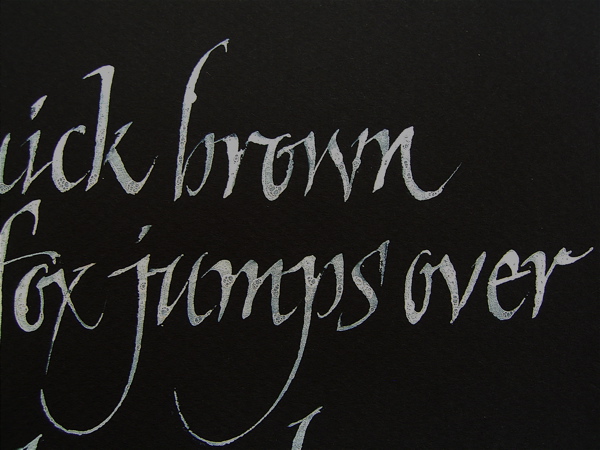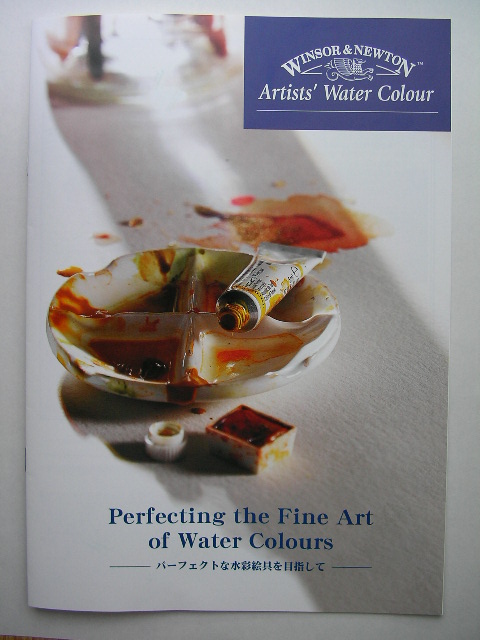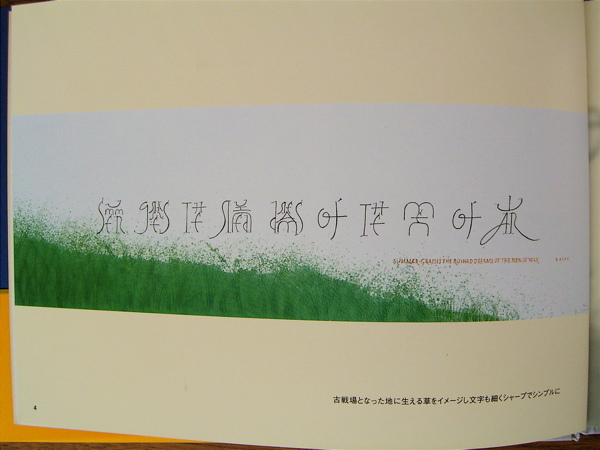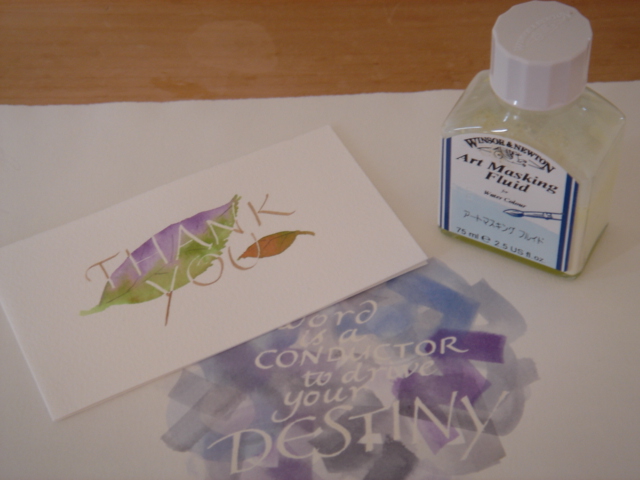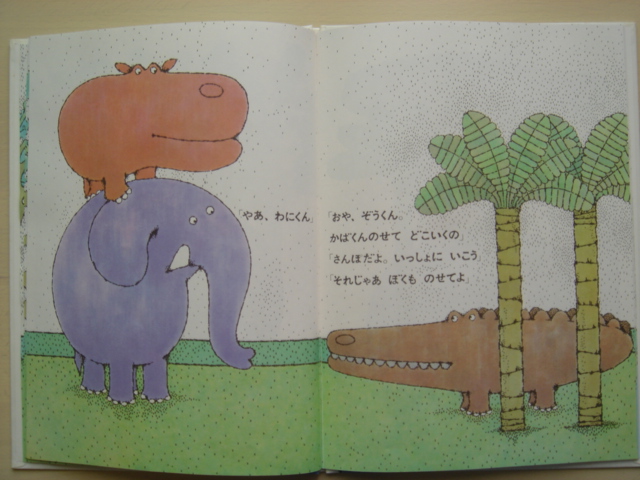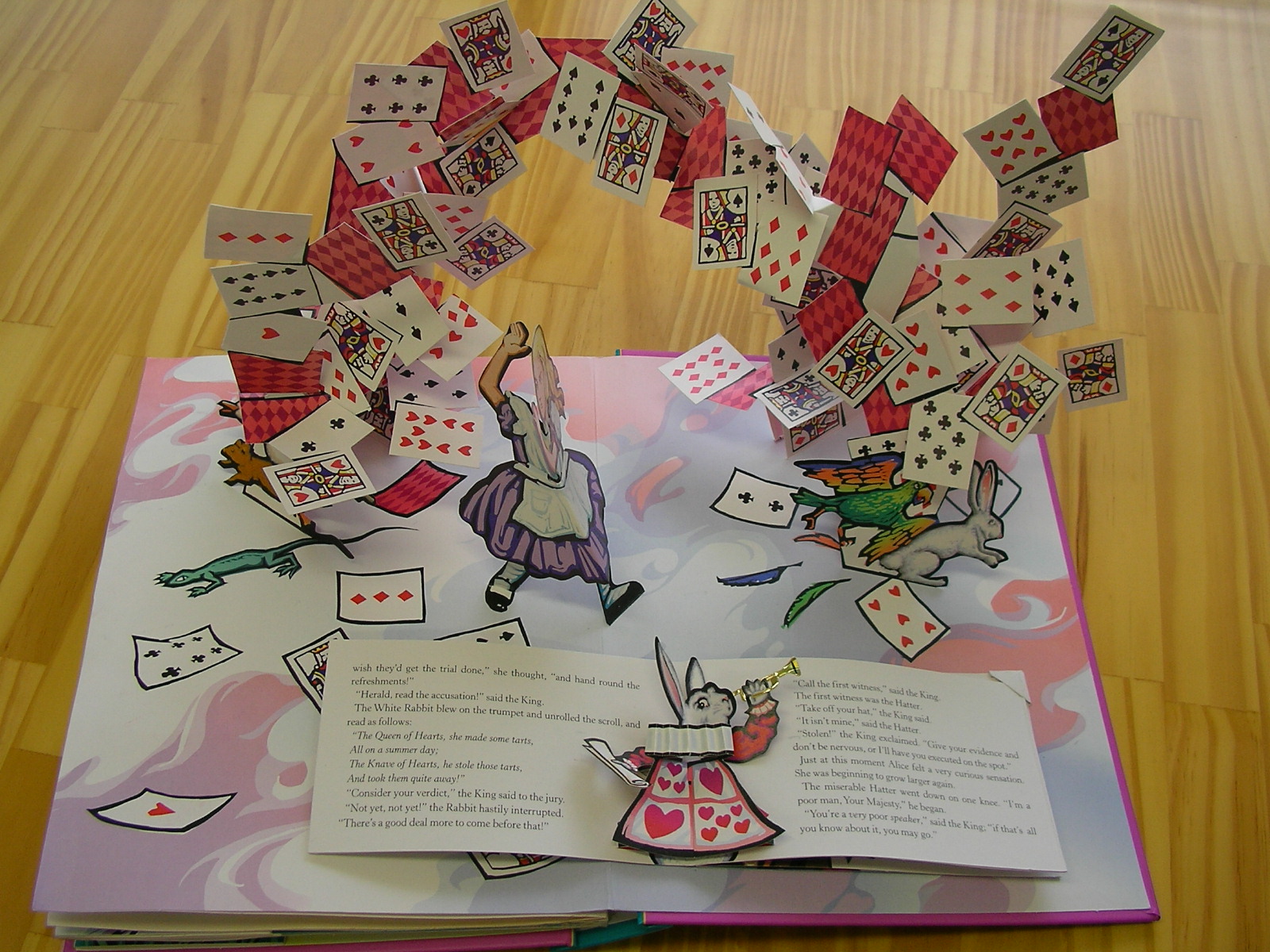
アルファベットのふきん
自由が丘のお店は3階でお食事とお茶ができ、1階、2階がショップになっています。帰り際に2階に寄り道。そこで見つけたのが、籐のかごにすました顔で並んでいたアルファベット柄のふきんです。少し重たい感じの書体ではありますが、何か可愛くて…つい購入してしまいました。いけない…また文字好きの癖が出てしまいました。
モジにかかわるある風景
スイスのサンモリッツという町で見かけたある風景…。
最初に通りかかったときは、おじさん大きなアルファベットと格闘中…。なるほど、こんな構造、こんなからくりだったのか…。ブラブラと風に揺れているB,T,Aがかわいらしい。おじさんのお取込中にハイ、パチリ
町の散策もだいたい終わり帰り道…。おじさんの姿は既になく、きれいなスペースでアルファベットが並んでいました。お店もオープンしていました。メデタシ、メデタシ!
町にはいろんな書体のアルファベットが自然な姿でいろんな場所におさまっていました…。やはり地元のモジなんだなぁ…と実感!その町の建物や雰囲気と合っていて…なんかいい感じでした。
ぞうくんのさんぽ
「ぞうくんのさんぽ」はロングセラーの絵本です。子どもが小さいときに本屋さんでみつけたのですが、店頭でおおおっと喜んでしまいました。
なぜならこの絵本は活字ではなく、レタリングなのです。このひらがなが並んだ感じがとってもかわいくて即購入。
せりふものんびりとした言い方の繰り返しで小さい子のハートをつかんでいるんだろうなあ。
「さんぽだよ、いっしょにいこう」とか「いいとも、いいとも」とか・・・人のよいぞうくんのゆったりした話し方に
ぴったりの文字たちなのです。
絵のほうも動物の色がさりげない渋さで親子共にお気に入りの1冊です。
英語版も出ているようなのです。そちらの文字はどうなんでしょう、どなたか読んだ方いらっしゃいますか?
白墨液
白のインクや絵の具はいろいろとありますが、先日白墨液というのを発見しました。開明という書道のメーカーから出ています。カリグラフィーでは、色の濃い紙に白で書く事はよくありますが、書道で白を使うって見た事がないなぁ・・・・と思っていました。
でも・・・なんだかどこかで見覚えがあるような・・・・・
そうだ!見た事ありました!ありました!
よく旅館の入り口の看板に「歓迎 モジトル御一行様」って書いてある、アレですね!
よく振ってお使い下さいと書いてあるので、思いっきり振ったら、アワだらけになってしまいました。そのまま書いたら、なんと!バブルの形がそのまま文字の中で乾いて、とても面白いことになりました。普通の練習用の黒インクでもアワが立ちますが、黒だから書いても目立たなかったのでしょう。画像ではよくわからないかもしれません。拡大してみてください。
ハクボク液と読むのかと思ったら、しろずみ液とフリガナがふってありました。黒の紙では、少し下が透けますが、黒板や鉄板、プラスチック板、ガラス板にものります、と書いてあります。いろいろと試してみましょう。
東西融合
ところで芭蕉の俳句で 夏草や兵どもが夢の跡 というのがありますが、画像はそれをFusion Letterとして、アルファベットを漢字のように表現した松木久美子さんの作品です。
英文訳は、Summer grasses the ruined dreams of the men of war です。
東西融合の不思議な形。どちらかと言うと漢字というよりハングル文字にも見えますね。
ひとつひとつをよ〜く見ると、アルファベットが裏返しになっていたり、セリフが強調されていたり、大文字と小文字が一緒に使われていたりと、漢字の雰囲気を表すためによく工夫されています。
アルファベットと日本の文字を融合させた文字のさきがけとしては、遠山由美さんのDual Letterが有名ですが、このFusion Letterはあくまでも漢字の構成に当てはめたブロック文字として書いた創作文字なのだそうです。
マスキング
マスキング液は乾くとゴム状になって紙の白色を絵の具から守ってくれます。上からおいた絵の具類がかわいたらゴム状になったものをはがすわけです。
乾いて固まったマスキング液をピリピリとはがすのが快感なのか・・・
淡い色をのせるのでたいした効果が出ないとわかっていてもやっているのでこれはもはや習慣?
私個人はウィンザーアンドニュートンのマスキング液が好みです。色が淡い黄色なので白い紙にのせたときに見にくいのですが細いラインでもきれいに抜けるように思います。ほかにはミツワの製品がポピュラーで大抵の画材店にあると思います。
はがすときは紙を傷めないようにそっと、ラバークリーナー(ペーパーセメントなどをはがすゴム)などを使って・・・と
教えられたのですが実際は指の腹でこすってボロボロっと落としています。断然速いし、水彩に限って言えばざらついたりはしません。
子どもでも楽しめるマスキング、出来上がりを楽しみに今日も塗り塗りしています。
WINSOR&NEWTON Artists' Water Colourパンフレット
絵の具をはじめ画材というものは、持っているだけで楽しいものですよね。 カリグラフィーを始めて、画材屋に足を踏み入れてからはまっている人も多いのではないでしょうか。海外のカリグラファーも来日の際、日本の画材屋の棚にずら〜っと並んだ様々なブランドの色とりどりの絵の具に感激するほど、日本の画材は、充実しているようですし、情報いっぱい、楽しく、時間を忘れてしまう空間です。
さて、画材については、インターネット検索や書籍で、情報、知識を得ることができますが、メーカーが作っている紙のパンフレットも、有効で、きれいな印刷、ご自由にお持ちくださいというとても魅力的なものです。 その中で、WINSOR&NEWTON Artist's Water Colourのパンフレット、Perfecting the Fine Art of Water Coloursーパーフェクトな水彩絵の具を目指してーは、水彩絵の具を世界で初めて世に出したW&Nならではの充実したパンフレットではないでしょうか。製造方法、顔料についての詳細、堅牢度に関するデータ、カラーチャート、メディウムと盛りだくさんの14ページです。カドミウム顔料および代用顔料や新しい絵の具、改良された絵の具、製造中止になった絵の具の理由、長所がわかる一覧は、納得のページです。隅まで読めば、絵の具の知識倍増でしょう。
山田正亮展
会期終了間際の山田正亮の展覧会を見に、府中美術館へ行きました。
山田正亮は、日本の抽象絵画のひとつの到達点を築いた、とパンフレットには書いてあります。
私は今まで彼の絵は見た事はありませんでしたが、会期間際に行けて本当によかったです。
展覧会では、静物(Still Life)の具体的な形が徐々に失われ、面からなる作品(Work B)へと変化し、そして彼の代表するストライプの絵画(Work C)へと移って行くその変遷がよくわかりました。
私が見に行ったその日、ものすごい雷雨で土砂降りだったせいもあって、広く静かな会場に、私以外に人はほとんどいませんでした。
静かなはずなのに雨の音がかすかにする会場。ストライプのいくつもの大きな作品に囲まれ、それらの前に立って平行な線と色の繰り返しを見ていると、なんだかソワソワ落ち着かないような、それでいてずっと見ていたいというような、不思議で面白い感覚。
雨が止むまでミュージアムショップで時間をつぶし、雨上がりの少し涼しくなった中帰宅しました。
展覧会の印象は、その展示物だけではなく、天候とか人ごみとか、その時の状況によってずいぶん変わるのだろうなぁーと思った一日でした。
ストライプの絵は、かなり長く心に残りそうです。
不思議の国のアリス ポップアップブック
本棚に入れておくだけではもったいない、みんなに見せたくなる(見せてます!)自慢の絵本、不思議の国のアリスのポップアップブックです。
大人も子供も、開いた人は誰しも、思わずにっこりしてしまう、ハッピーになれること間違いなし。おいしいものに出会ったときと同じですね!
Robert Sabudaのポップアップは、どのページも芸術的、なかでもこのトランプのページは、感激!絶対買うぞ気分にさせるでしょう。(事実、私は、買ったわけです!) しかし、よくまあ、このようなことができるとは、手にして、目にして感激するだけでなく、感心しきりです。これを見る人は、前からだけでなく、いろいろな角度から見てワクワクするんです。お話が書かれているページも、凝ったポップアップになっているので楽しいです。
他に、落ち着いたミュートカラーのポップアップ絵本、The movable Mother Gooseもすてきです。
ポップアップは、絵本だけでなく、印刷物のデザインにも広く使われている手法ですが、カリグラフィーの世界でも、関心、興味の対象です。文字をデザインしてポップアップにしたり、本の制作や簡単なテクニックをカードに応用したりして使われています。カリグラフィー専門海外通販ショップのカタログにも、Robert Sabudaの本は、数冊載っています。他に、日本の白い一枚の紙から切り出す折り紙建築も、ポップでカラフルなものとは、また違った味わいで、美しく、すばらしいものです。
この写真は、パッとせず残念です。でも、画像は、いろいろなところで見れます。街でも、結構出会えます。ただし、ビニールが、かかっているかも....